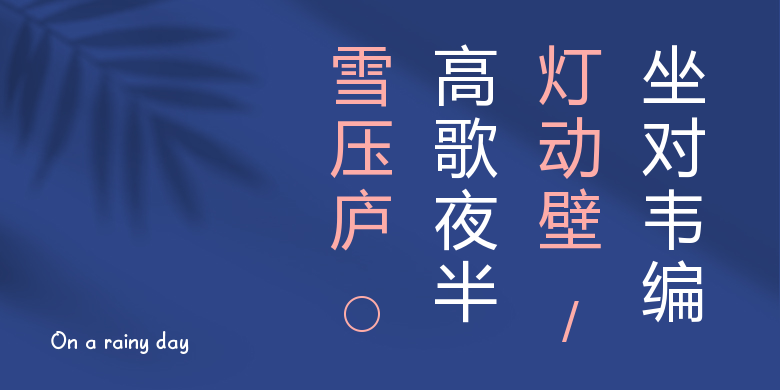
On a rainy day
On a rainy day,这款字体结构工整、笔画清晰,兼顾美观与易读性,适用于标题、正文、海报、包装、LOGO 等多种场景。字形优雅稳定,风格百搭耐看,适配日常排版与创意设计,让文字呈现更舒适、更具质感。On a rainy day一笔一画,皆是细节,以均衡的比例、流畅的线条打造舒适视觉体验,字形端正大气,风格简约现代。无论是商业设计、品牌宣传还是日常排版,都能轻松驾驭,让文字更有格调与力量。On a rainy day字体下载。